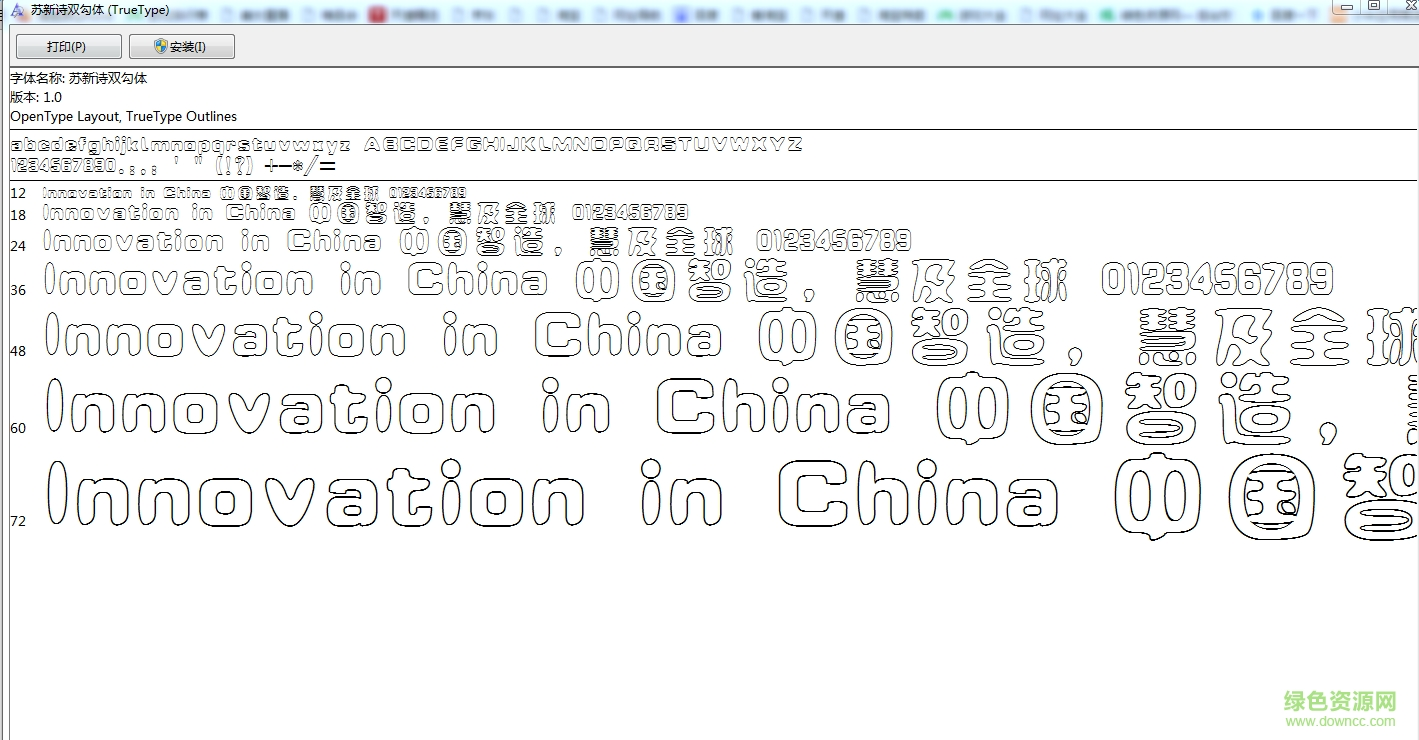
蘇新詩雙勾體字體是一款獨(dú)特的空心字體,線條圓潤(rùn)流暢,可適用于商品包裝和廣告設(shè)計(jì)方面,有興趣的朋友快來綠色資源網(wǎng)下載吧!
蘇新詩雙勾體是一款應(yīng)用于設(shè)計(jì)方面的中文簡(jiǎn)體字體,采用了空心設(shè)計(jì),字形美觀,角邊圓潤(rùn),可以應(yīng)用于產(chǎn)品包裝、平面廣告、企業(yè)專用、名家題字等領(lǐng)域,喜歡的用戶可下載收藏。